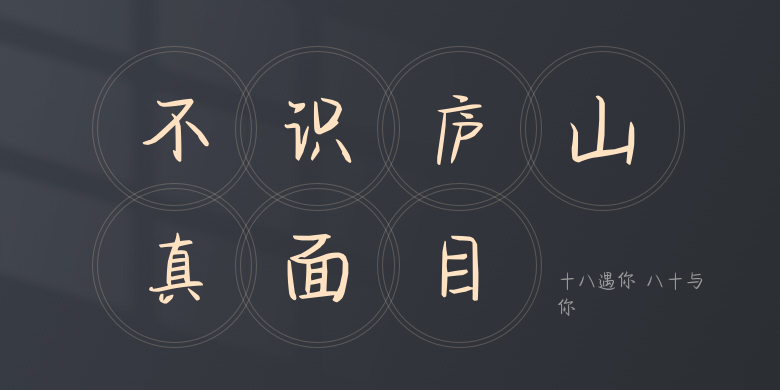
十八遇你 八十与你
十八遇你 八十与你,这款字体结构工整、笔画清晰,兼顾美观与易读性,适用于标题、正文、海报、包装、LOGO 等多种场景。字形优雅稳定,风格百搭耐看,适配日常排版与创意设计,让文字呈现更舒适、更具质感。十八遇你 八十与你一笔一画,皆是细节,以均衡的比例、流畅的线条打造舒适视觉体验,字形端正大气,风格简约现代。无论是商业设计、品牌宣传还是日常排版,都能轻松驾驭,让文字更有格调与力量。十八遇你 八十与你字体下载。